25 migliori font Art Déco 2023 (gratuiti e premium)
Pubblicato: 2023-04-06Quali sono i migliori font Art Déco per far risaltare i tuoi design? Caratteri classici e senza tempo o qualcosa di moderno e unico, ce n'è per tutti i gusti.
Non sorprende che l'Art Déco stia riguadagnando popolarità in questi giorni, con i designer che cercano di incorporare i suoi elementi classici nei loro progetti. Puoi trovare tonnellate di font Art Déco online, sia che tu voglia qualcosa di elegante e senza tempo o qualcosa di spigoloso e moderno.
Qui esploreremo alcuni dei migliori font Art Déco e mostreremo come utilizzarli nei tuoi progetti.
I migliori font Art Déco Premium
Dagli eleganti serif, ai caratteri di visualizzazione in grassetto e tutto il resto, il nostro elenco contiene alcune delle migliori opzioni premium in circolazione per creare splendidi design con un'estetica vintage.
Quindi, che tu stia progettando un logo, un invito o un sito Web, dai un'occhiata al nostro elenco dei migliori font art deco qui sotto e trova la soluzione perfetta!
AVVENIDA
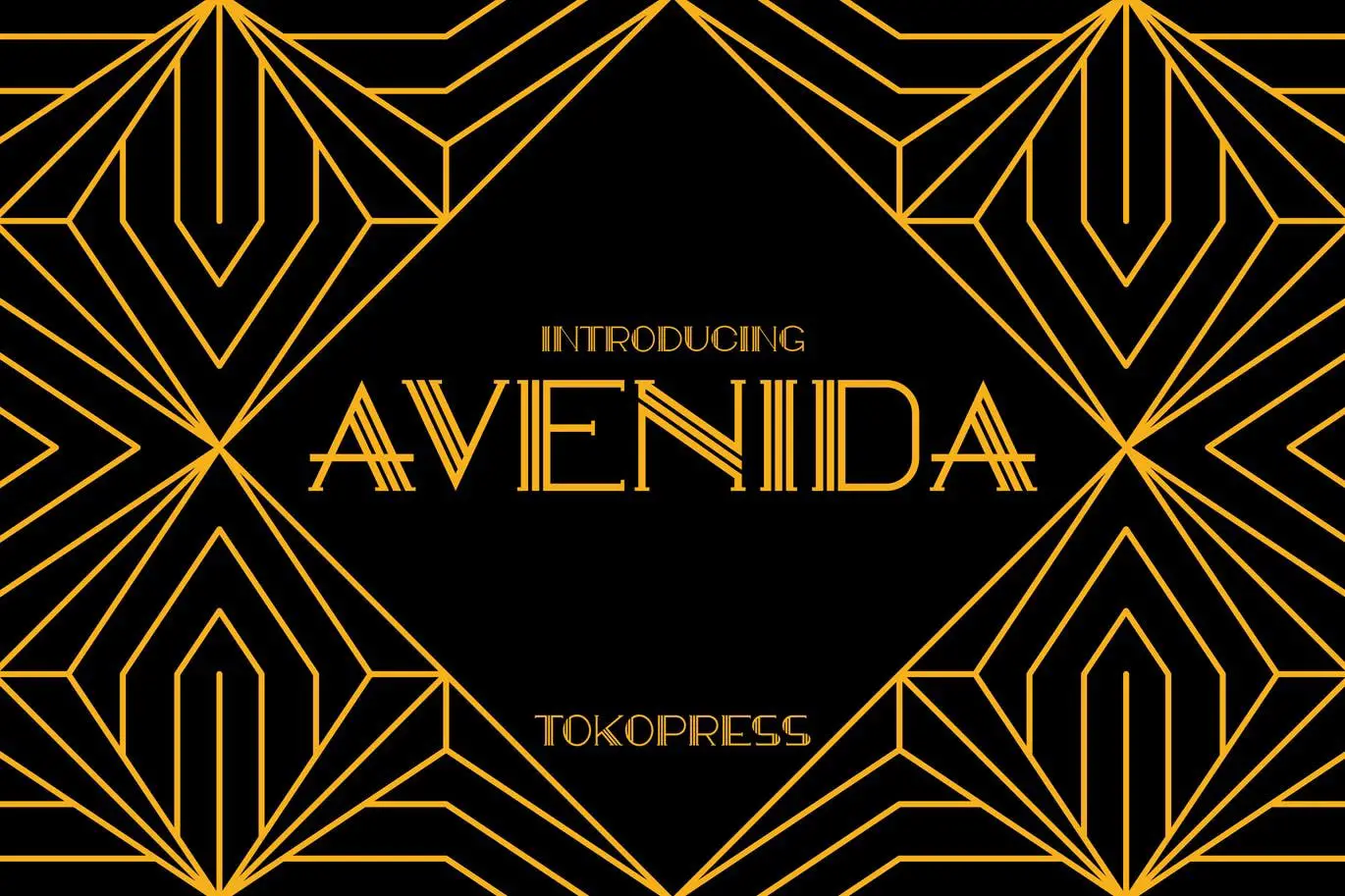
'AVENIDA' è un carattere Art Déco classico, elegante e di alta classe. È ottimo per design di poster, titoli di film, menu classici, copertine di riviste e YouTube, miniature e copertine di social media. Con AVENIDA, il tuo progetto avrà un aspetto elegante e sofisticato
È perfetto per chi cerca un carattere sofisticato e senza tempo. Che tu sia un designer che crea un poster o un imprenditore che mira a stupire i tuoi clienti con un design straordinario, questo carattere art déco si distingue totalmente.
Houstone - espanso / esteso
Houstone - ampliato / esteso Art Deco Sans Serif - Retro Vintage Architectural Historical Display Font è la scelta perfetta per qualsiasi progetto di design. è uno dei bellissimi caratteri Art Déco che offre un tocco vintage unico ed elegante che porterà un ulteriore livello di raffinatezza ai tuoi progetti.
Sia che tu stia cercando di creare un logo, un design editoriale, un design sportivo, un'industria dei videogiochi, un poster musicale, un design storico, un design architettonico e di mobili, un design di un sito Web, un design pubblicitario moderno, una citazione di poster, un titolo di libro/copertina o eventi speciali design, questo tipo di carattere ti ha coperto.
Il carattere Houstone è appositamente progettato per far risaltare il tuo testo. È dotato di glifi estesi, che gli conferiscono maggiore portata e versatilità rispetto a molti altri caratteri, oltre a un'ampia varietà di opzioni e legature di caratteri alternativi. Questo font è ottimo anche per ottenere un look retrò e vintage. Le sue lettere in grassetto e le sue forme geometriche evocano uno stile art déco iconico che ha un bell'aspetto sia nelle applicazioni digitali che in quelle stampate.
Delauney
Puoi aggiungere un tocco di lusso ed eleganza a qualsiasi progetto di design con Delauney, un carattere Art Déco. Con il suo aspetto geometrico e tratti decisi, Delauney ha un'estetica minimalista e caratteristiche OpenType. Ha caratteri accentati e funzionalità OpenType che gli danno molto da scegliere.
Lo stile normale è ideale per titoli o titoli, mentre lo stile ombra aggiunge un ulteriore livello di raffinatezza. Lo stile Catchwords è disponibile in tre lingue (inglese, spagnolo e bahasa) e può essere utilizzato per rendere le parole più decorative.
Esposizione della canonica
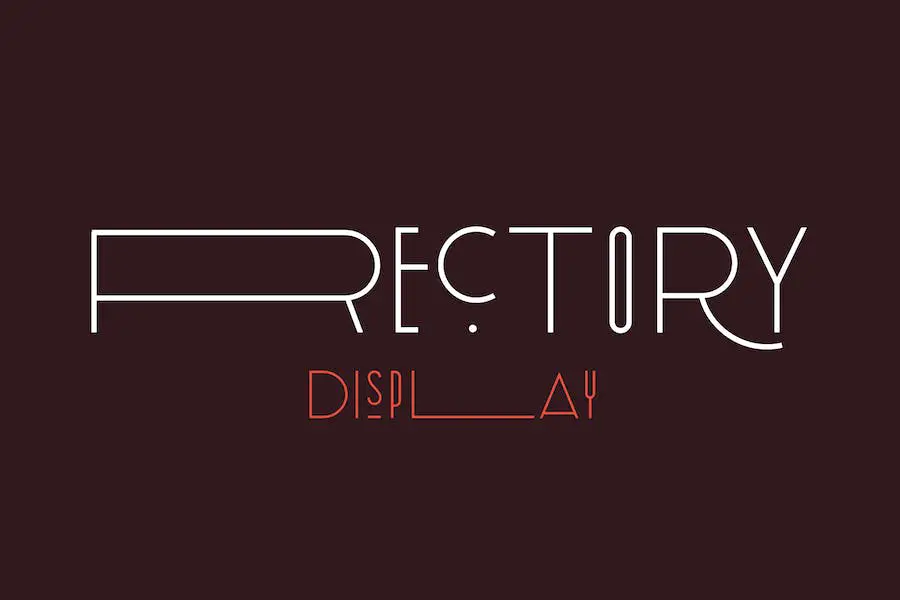
Rectory Display aggiungerà un tocco retrò unico a qualsiasi progetto, fornendo anche funzionalità moderne. È perfetto per mettere in risalto titoli o intestazioni e la funzione WOFF del carattere Web è preziosa per i progetti online. Le legature e i glifi unici offrono molte opportunità per creare design accattivanti.
Viene fornito con glifi maiuscoli e minuscoli, punteggiatura, numeri e supporto multilingue, oltre a legature uniche e carattere web WOFF. È uno dei font Art Nouveau facile da usare, versatile e offre grandi opportunità per personalizzare il testo.
DECORA
DECORÁ è un bellissimo carattere geometrico ispirato all'era Art Déco degli anni '20. Le sue caratteristiche principali sono il lusso, le linee pulite, grandiose, eleganti, moderne, ricche, geometriche, progressiste e speranzose. Questo tipo di carattere è perfetto per il design di packaging di lusso, inviti, loghi, branding e altro ancora.
Questo tipo di carattere ti offre una vasta gamma di opzioni per adattarlo al tuo design. Puoi scegliere tra più pesi, dimensioni e stili in modo che il tuo design sia perfetto. Il carattere presenta anche funzionalità OpenType in modo da poterlo personalizzare ancora di più.
Carattere tipografico Decohead
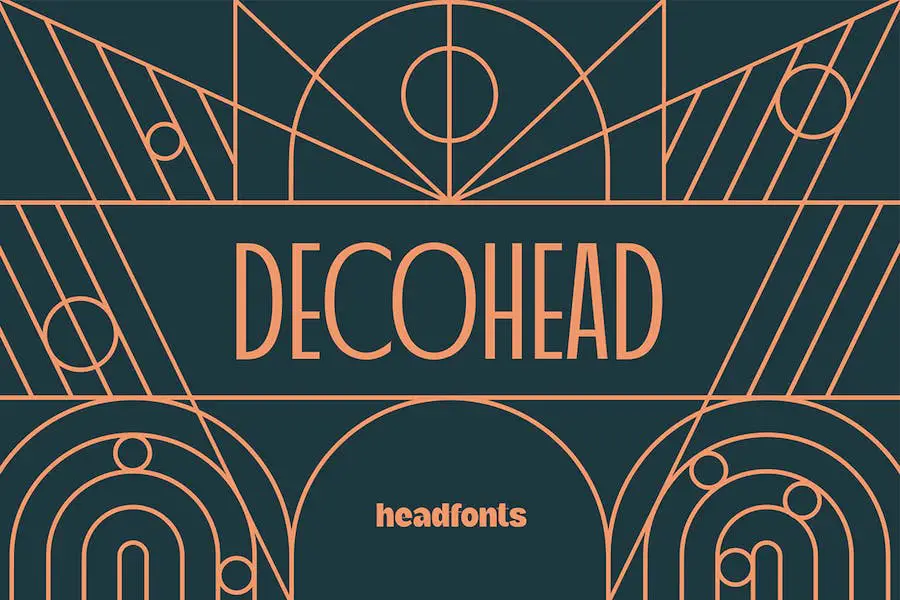
Decohead Typeface è un bellissimo carattere tipografico ispirato all'Art Déco, perfetto per aggiungere eleganza e glamour a qualsiasi progetto di design. Il carattere viene fornito con tre pesi, caratteri maiuscoli e minuscoli e 63 glifi per carattere e supporto di caratteri latini standard con numeri.
Con il suo tocco unico e delicato può portare raffinatezza ai progetti più esigenti, da poster, intestazioni e loghi femminili a inviti di nozze e altro ancora. Decohead si distingue dalla massa combinando modernità con caratteri tipografici decorativi, dando un aspetto generale squisito che non sarà troppo squallido.
DECONICO
DECONICO è un font dall'aspetto art déco che parla di eleganza, classe e raffinatezza. È il carattere perfetto per progetti di fascia alta come poster, titoli di film, menu per ristoranti e caffè classici, copertine di riviste, miniature di YouTube e copertine di pagine di social media.
Con il carattere DECONICO, puoi essere certo che ciò che disegni si distinguerà sempre dalla massa. Ha una qualità senza tempo e può essere facilmente personalizzato per soddisfare le vostre esigenze di design.
Rosalina
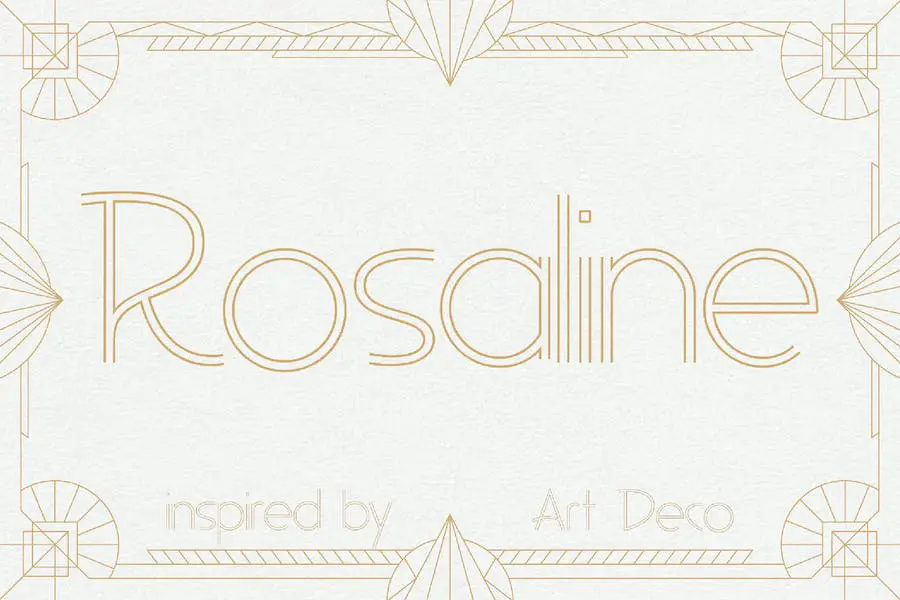
Rosaline è un fantastico font Art Déco che offre grande leggibilità, versatilità e stile. È perfetto se stai facendo qualcosa di vintage o qualcosa di più moderno
Oltre ad avere un bellissimo disegno del contorno, il carattere è super elegante. Oltre ad essere di facile lettura, le sue forme delle lettere sono progettate per essere facilmente leggibili anche a piccole dimensioni, conferendole un fascino senza tempo che non passerà mai di moda.
In termini di versatilità, Rosaline è un'ottima scelta. Sembra altrettanto buono nei titoli grandi come nel corpo del testo. Per quanto riguarda lo stile, hai molte opzioni. Puoi regolare il tracciamento, l'interlinea, la crenatura e altro per creare esattamente l'aspetto che desideri. C'è anche una gamma di caratteri e legature alternativi disponibili per una maggiore personalità.
Casa Braga
Con Braga Huis troverai tre diversi stili di carattere: maiuscolo, minuscolo e varie opzioni alternative basate sulla famosa strada di Bandung, nelle Indie Olandesi. Ha un forte carattere Art Déco ed è disponibile in tre stili: maiuscolo, minuscolo e alternative. L'atmosfera ottocentesca è catturata dalle linee forti e dalla passione sinuosa di Braga Huis.
Le sue caratteristiche lo rendono perfetto per creare poster o qualsiasi altra forma di opera d'arte. Con i suoi elementi strutturali dettagliati, il livello avanzato di design e lo stile art déco, Braga Huis non sarà mai fuori moda, non importa come passa il tempo. Le sue opzioni personalizzabili consentono agli utenti di personalizzare davvero questo carattere.
POCHTER
Pochter è un carattere tipografico unico ispirato allo stile Art Déco. Viene fornito con un file OTF e TTF, oltre al supporto multilingue per lettere maiuscole e minuscole, numeri e punteggiatura.
questo font ha un aspetto classico: il design è moderno ma elegante e lo rende un font perfetto per una vasta gamma di progetti. È facile da leggere con lo spazio tra ogni lettera. Inoltre, i numeri aggiungono un tocco speciale a qualsiasi progetto, poiché sono piuttosto decorati nel design. Pochter ha un supporto multilingue che rende possibile utilizzarlo in molte lingue diverse per una varietà di progetti.
Burges – Classico
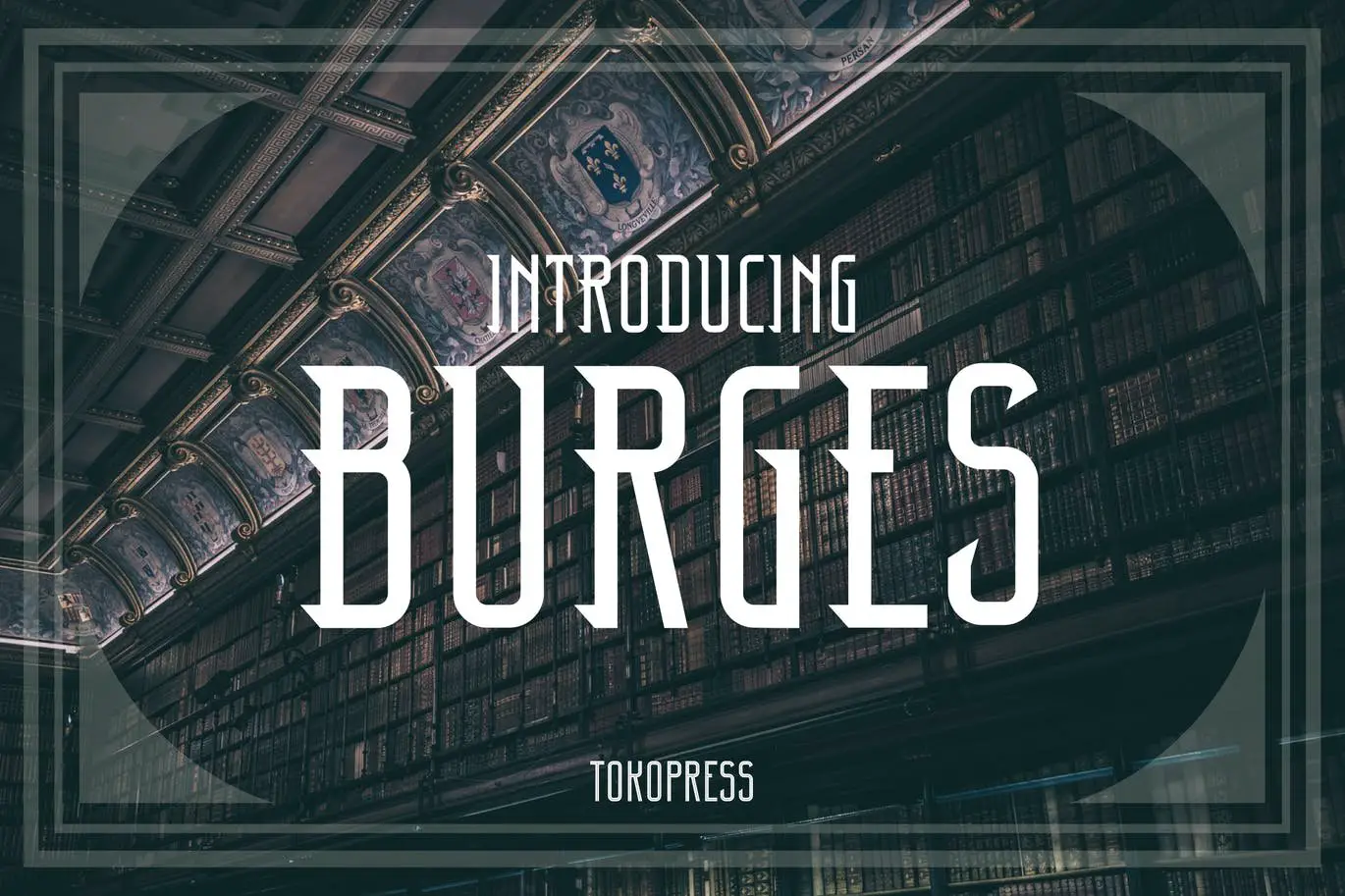
In Burges - Classic ottieni un tocco vintage tra i solidi caratteri maiuscoli e minuscoli in linea. Puoi usarlo per poster, titoli di film, menu di ristoranti, copertine di riviste, miniature di YouTube e molto altro.
I caratteri Google Art Déco sono facili da leggere e hanno un bell'aspetto in titoli e titoli di grandi dimensioni. Le forme delle lettere sono molto distinguibili e equidistanti, rendendolo altamente leggibile anche a dimensioni più piccole. Ha un aspetto senza tempo che si adatta facilmente a qualsiasi design.
Oltre alla sua versatilità, Burges – Classic può essere utilizzato in una varietà di stili, da quello audace e accattivante a quello sottile ed elegante. Questo tipo di carattere funziona bene per i design retrò e per i layout moderni.
Linea del ponte
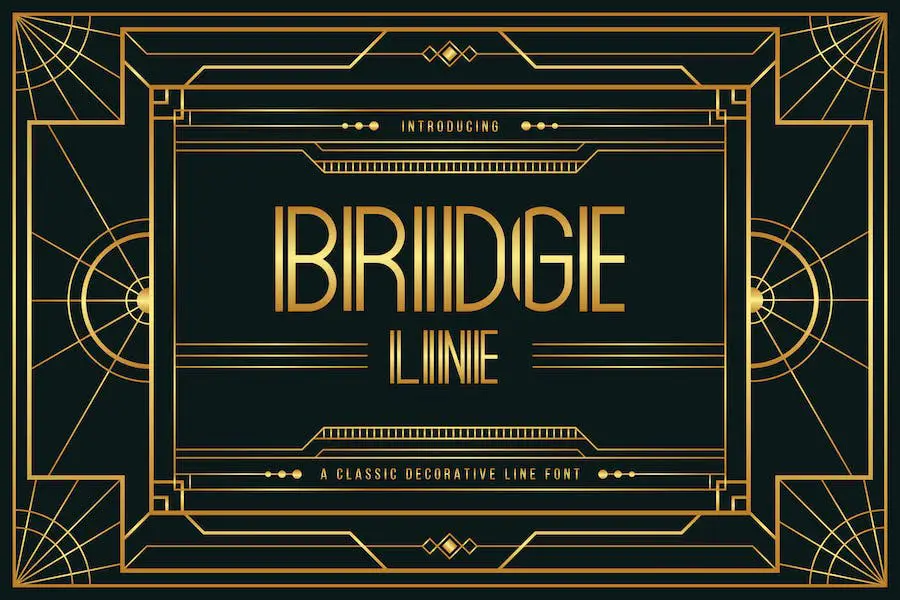
C'è qualcosa di speciale nel carattere art deco Bridge Line per il suo aspetto audace e solido. Avere uno stile geometrico vintage lo rende ideale per una varietà di applicazioni, come titoli di film, identificazioni di marchi ed eventi. Con la sua vasta gamma di funzioni, Bridge Line è destinata ad aggiungere un tocco di stile al tuo design.
È classico e senza tempo, ma abbastanza moderno da poter essere utilizzato in design contemporanei. La sua natura versatile lo rende utile sia per la stampa che per il digitale. Viene fornito con alternative e legature per qualsiasi design.
Club dei miliardari
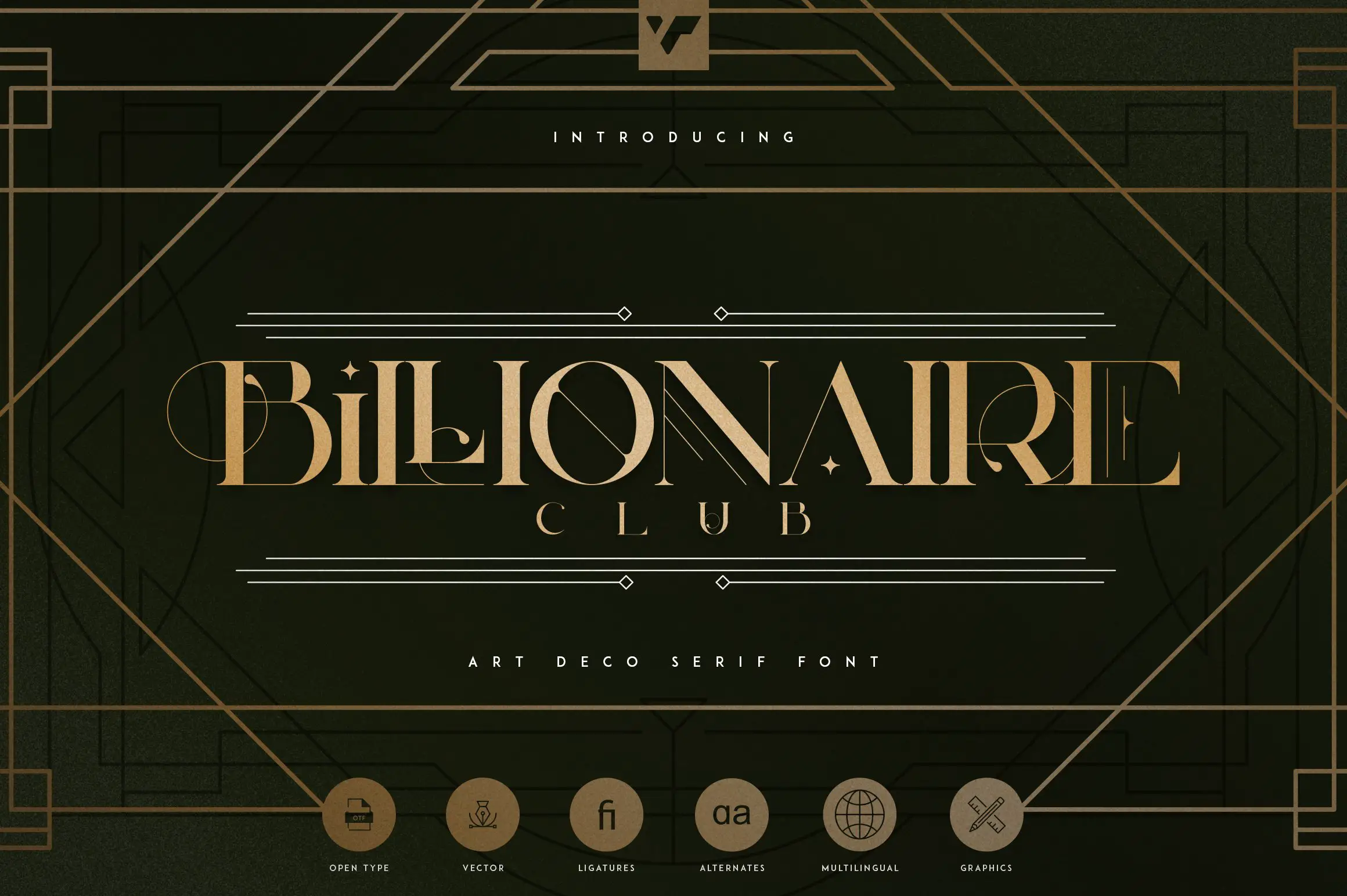
Il carattere tipografico Art Déco Billionaire Club è dotato di 8 glifi alternativi, 6 cornici e linee, oltre al supporto multilingue in modo da poter dare un tocco glamour ai tuoi progetti.
Che tu stia marchiando un progetto, progettando articoli per la casa, confezionando prodotti o creando intestazioni di riviste, Billionaire Club sarà il tuo font preferito. Ha un bell'aspetto in formati grandi e piccoli e il suo stile versatile lo rende facile da usare come sovrapposizione su qualsiasi immagine di sfondo.
La parte migliore di Billionaire Club è che è incredibilmente facile da usare. I caratteri sono ben fatti e le cornici e le linee sono precise e chiare. Inoltre, con il supporto multilingue, puoi utilizzare questo font in quasi tutte le lingue.
Avoner
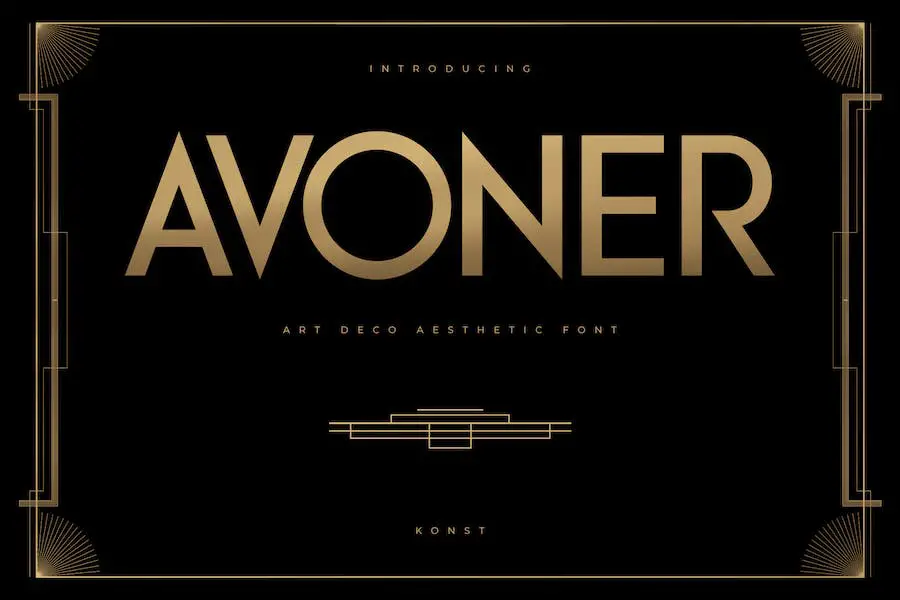
Avoner è un font art déco moderno perfetto per loghi, marchi e riviste. È ispirato alle immagini e alla pubblicità degli anni '30 ed è un font tutto maiuscolo.
Questo tipo di carattere è ottimo per l'estetica di alta moda, i gioielli, i profumi, il trucco, i cosmetici o i caratteri Adobe art deco. Nonostante il suo stile unico, questo carattere aggiunge un tocco senza tempo a qualsiasi progetto poiché è scritto in inglese. È anche conveniente per una varietà di progetti perché è disponibile in così tante lingue
USIGNOLO
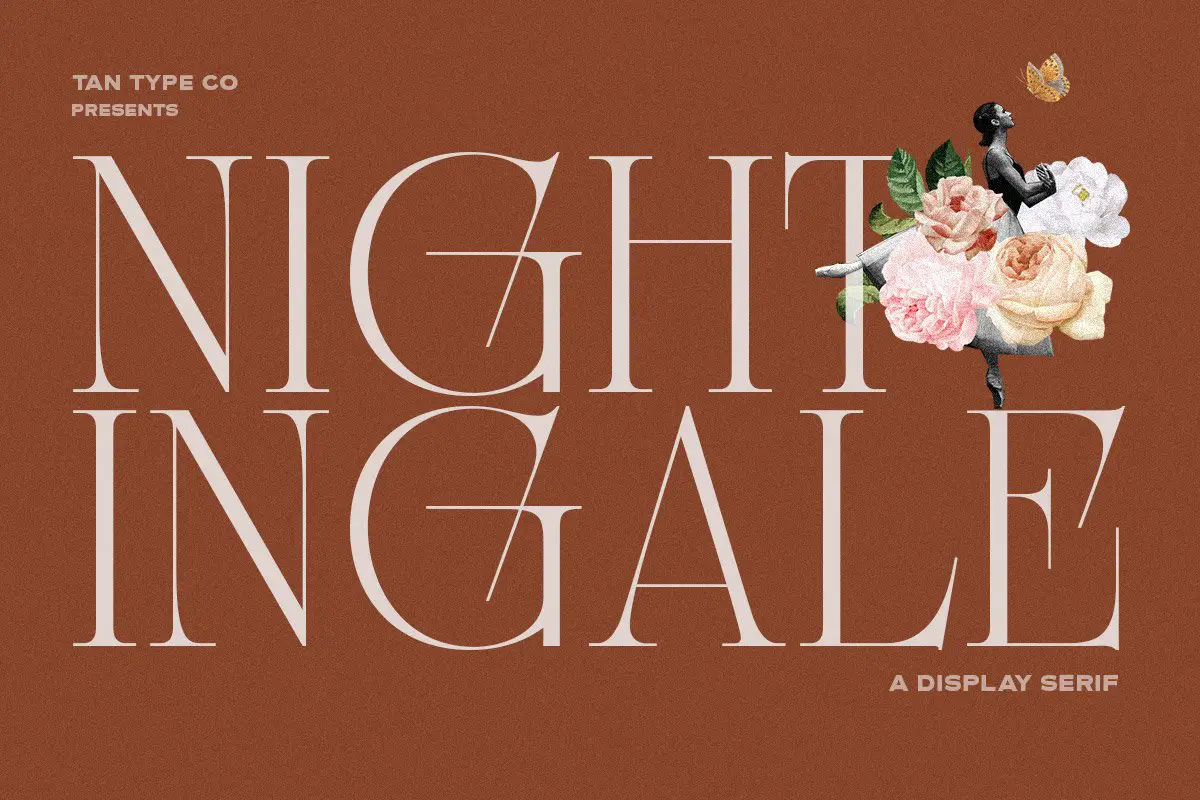
Un carattere art déco con serif notevolmente allungati, NIGHTINGALE aggiunge un'eleganza pulita e moderna a qualsiasi design, creando un'estetica unica con sottigliezza e raffinatezza allo stesso modo.
È versatile e adattabile sia per taglie piccole che grandi grazie ai suoi audaci serif. Lo stile distinto di Nightingale evoca mistero e aggiunge lusso a qualsiasi progetto. Ti distinguerai dalla massa con Nightingale, sia che tu stia creando un logo o un titolo.
Bagiewise
Bagiewise è un font display art déco che offre un look vintage audace, solido ed elegante. Perfetto per inviti, banner, titoli di film, marchi ed eventi, Bagiewise aggiungerà sicuramente un tocco classico a qualsiasi progetto.
Ha un forte look retrò con le sue linee pulite e le forme classiche, quindi è perfetto per i design moderni. Il carattere è facile da leggere, ma è facile da usare. Puoi ottenere Bagiewise in una serie di pesi e stili, quindi se stai cercando un font con un aspetto distintivo, questo è il meglio dell'art deco, questo è il font che fa per te.
Brilon
Il carattere Brilon è un elegante serif ispirato all'era Art Déco. Con il suo design moderno e l'estetica minimalista, sarai in grado di creare loghi, packaging e inviti che sembrano senza tempo con speciali lettere maiuscole, caratteri alternativi e bellissime legature.
Per rendere le cose ancora migliori, questo font viene fornito con 8 foto botaniche per una presentazione completa. Se stai cercando un carattere unico con un tocco classico, vale sicuramente la pena dare un'occhiata a Brilon.
Che tu stia creando loghi e marchi o inviti e cancelleria, Brilon ha un design versatile che può essere utilizzato in tutti i tipi di progetti.
Serendior
Serendior è uno straordinario set di caratteri e motivi di Zeune che si ispira al movimento Art Déco. Vanta due stili distinti, Block e Stroke, e contiene più di 400+ glifi con supporto multilingue. La combinazione di Costruttivismo, Futurismo e Art Déco rende il design di Serendior davvero unico.
Serendior si distingue tra gli altri caratteri per le sue legature discrezionali e set stilistici. Ciò consente agli utenti di creare design personalizzati e aggiungere un tocco in più al proprio lavoro. Inoltre, i caratteri sono stati realizzati con cura e precisione, conferendo loro una finitura professionale.
VOLTDECO
Un carattere moderno ispirato all'Artdeco, VolTDECO aggiunge un tocco in più a qualsiasi design. Con le sue linee audaci e il look classico che incontra il contemporaneo, è perfetto per loghi, poster, insegne, siti web, ecc.
Il carattere ha molte opzioni di stile come ornati, legature, alternative e altro, quindi è perfetto sia per progetti formali che informali. Le sue forme uniche daranno a qualsiasi design un tocco in più. Chiunque cerchi uno stile classico dovrebbe dare un'occhiata a VOLTDECO.
Genesi
Genesis è un'ottima scelta per chiunque cerchi un carattere tipografico ispirato all'art déco. È un carattere condensato che sembra ancora moderno e sofisticato, fornendo il carattere appena sufficiente per far risaltare il tuo design. Con oltre 50 legature, offre molta versatilità in modo da poter creare splendidi design senza passare ore a cercare la combinazione di lettere perfetta.
Lo stile sobrio lo rende ideale per branding, titoli, riviste, stampa, libri e altro ancora. Che tu sia un designer professionista o che tu abbia appena iniziato nel settore, Genesis è un'ottima opzione per portare vibrazioni art déco al tuo prossimo progetto.
I migliori font Art Déco gratuiti
Abbiamo cercato in alto e in basso per offrirti un elenco dei font art deco GRATUITI più apprezzati, in modo che tu possa trovare il carattere tipografico perfetto per soddisfare le esigenze del tuo progetto.
Che tu stia cercando un carattere classico o qualcosa di più unico, troverai sicuramente quello giusto qui!
Déco artigianale
'Artistic Deco' è un carattere tipografico serif vintage perfetto per progetti di branding, titoli, poster e imballaggi. Si ispira alle copertine di riviste vintage degli anni '20, conferendole uno stile classico ed elegante. Ogni versione ha il suo stile e la sua atmosfera unici.
Indipendentemente dalla versione scelta, questo carattere tipografico è stato progettato per la massima leggibilità. Le curve sottili aiutano a guidare gli occhi in modo naturale attraverso la pagina, mentre i tratti ascendenti e discendenti alti fanno risaltare il carattere. Inoltre, l'uniformità tra le lettere emana un aspetto organizzato e professionale che renderà qualsiasi progetto lucido e raffinato.
Odalisca
Odalisque è un bellissimo font ispirato allo stile art déco degli anni '20. Traendo ispirazione dal lavoro di Morris Fuller Benton e dei fondatori di American Type, Odalisque fonde raffinatezza elegante con un tocco artistico e artigianale. Include i set di caratteri Unicode Latin 1252 e 1250 dell'Europa centrale, oltre al supporto per la localizzazione per moldavo e rumeno.
Questo carattere elegante ha un bell'aspetto nei titoli e nei titoli ed è perfetto per aggiungere un tocco di glamour del vecchio mondo a poster, volantini e biglietti di auguri. Ha anche abbastanza sottigliezza per essere utilizzato in design più delicati, come inviti di nozze o copertine di libri. Con la sua vasta gamma di personaggi, Odalisque farà sicuramente risaltare qualsiasi progetto.
Neve calda
Elegante e audace, Hot Snow offre. Con i suoi design di ispirazione vintage e le forme dei caratteri distintivi, questo font si distinguerà dalla massa. Puoi personalizzare molto con la codifica PUA poiché sarai in grado di accedere a tutti gli ornati e glifi.
Che tu stia creando loghi, poster o qualsiasi altra cosa, Hot Snow darà vita al tuo design. Le sue linee audaci e i personaggi potenti assicurano che la tua creazione si distingua dal resto. Aggiungilo a qualsiasi progetto, grande o piccolo, e lascia che Hot Snow lo porti al livello successivo.
Display Compot
Puoi utilizzare Kompot Display per creare design accattivanti. È dotato di glifi alternativi, legature e supporto multilingue, quindi puoi usarlo grande o piccolo.
Con il supporto per set di caratteri latino di base, latino avanzato, cirillico di base e cirillico avanzato, Kompot è il carattere tipografico perfetto per progetti di branding, design di decorazioni per la casa, confezioni di prodotti, intestazioni di riviste e altro ancora.
Crescendo
Caratterizzato da spigoli vivi e linee sottili e curve, Crescendo ha un aspetto vintage con le sue forme monoline che bilanciano caratteristiche classiche e contemporanee.
Con oltre 800 glifi, questo carattere tipografico offre varie funzionalità OpenType come alternative contestuali e ornati. Inoltre viene fornito con diverse opzioni di supporto linguistico e legature. Ciò semplifica la creazione di design espressivi che si distinguono dagli altri.
Domande frequenti
Il carattere tipografico Art Déco si è sviluppato negli anni '20 ed è famoso per le sue forme geometriche, le linee audaci e l'estetica modernista generale. Le forme geometriche semplificate tendono ad essere viste come ornamenti sul carattere.
Si ritiene che il carattere Art Déco sia stato sviluppato per la prima volta in Francia all'inizio del XX secolo, ma abbia guadagnato popolarità in America durante gli anni '20, principalmente nella progettazione di stampe commerciali e pubblicità, diventando anche uno degli stili di carattere più famosi durante quei decenni.
Quando scegli un font art deco, considera lo scopo del tuo design. È per un logo? O più un elemento decorativo? I caratteri Art Déco possono essere disponibili in una varietà di stili che vanno dal tradizionale al moderno, quindi assicurati di sceglierne uno che si adatti alle esigenze specifiche del tuo progetto.
Ci sono molte ragioni per cui un carattere Art Déco si distingue dal resto dei caratteri sul mercato. Forme e linee audaci e geometriche, insieme a un'estetica senza tempo, è ciò che rende i caratteri tipografici Art Déco così distinti tra un mare di altri stili.
Conclusione
Qui discutiamo i migliori font Art Déco per i tuoi progetti. Discutiamo le loro caratteristiche e forniamo suggerimenti su come selezionare il carattere giusto.